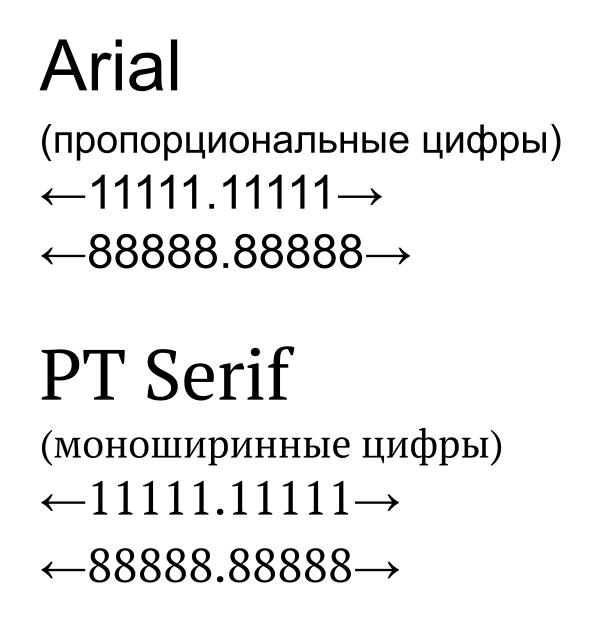
Моноширинный шрифт
Моноширинный, или непропорциональный шрифт, — шрифт, в котором все знаки (точнее, кегельные площадки знаков) имеют одинаковую ширину[1]. Этим он отличается от пропорционального шрифта, в котором буквы отличаются по ширине друг от друга[2].
Следует различать моноширинный и равноширинный шрифты: в последних знаки стремятся к одинаковой ширине, но кегельные площадки знаков неодинаковы[3].
История
Пишущие машинки
Первые моноширинные шрифты были разработаны для пишущих машинок, так как реализация механической печати пропорциональным шрифтом требовала значительного усложнения печатающего узла[4]. Существовали и наборно-печатающие машинки, использующие пропорциональный шрифт и изменение межбуквенных интервалов, но они применялись лишь в оперативной полиграфии[5]. Конструкция электромеханических печатных машинок и телеграфных аппаратов в большинстве своём также предполагала использование моноширинных шрифтов.
Компьютеры
Жизнь моноширинных шрифтов продолжилась на компьютерах: в качестве устройства ввода-вывода во многих ранних ЭВМ использовался телетайп[6][7]. Долгое время алфавитно-цифровые печатающие устройства (например — принтеры типа «ромашка») и знакогенераторы видеотерминалов и графических адаптеров также позволяли использовать исключительно моноширинные шрифты. Текст на экран выводился в виде матрицы знакомест, в которую могло поместиться строго определённое количество знаков (как правило, 80 символов в строке, что соответствовало объёму одной перфокарты), а видеоизображение динамически создавалось по кодам символов и их изображениям — это давало экономию дорогой (в те времена) памяти и упрощало программирование.
В наборы символов подобных устройств часто включались также символы псевдографики для оформления разного рода таблиц и бланков, а также простых графиков и рисунков[8]. В дальнейшем моноширинные шрифты и псевдографика легли в основу расширенного текстового интерфейса пользователя, включающего в себя элементы оконного.
Особенности начертания символов
Буквы многих алфавитов (латинского — в большей степени, современного русского — в меньшей) имеют разную ширину знаков. Некоторые знаки (такие, как i) занимают в кегельной площадке место шириной в один основной штрих, а другие (такие, как w) — в несколько раз больше[3]. Поэтому вокруг узких знаков образуется много пустого места, а широкие становятся тёмными и сложноразличимыми, особенно в небольшом разрешении и жирном начертании.
Чтобы эти недостатки не были столь заметны, к буквам применяются дополнительные меры оптической компенсации. Узким буквам добавляют засечки, даже если остальные символы шрифта выполнены без засечек[4]. У широких символов иногда уменьшают некоторые элементы, как средний штрих у буквы «Ш». Ещё при проектировании моноширинных шрифтов возникает проблема схожести цифры 0 и буквы O, и чтобы их можно было отличить, первую нередко перечёркивают по диагонали, либо вносят другие элементы внутрь овала.
Все эти меры искажают привычный рисунок букв[4]. К тому же строки, набранные моноширинным шрифтом, не выглядят сплошными, а разбиваются на колонки шириной в одно знакоместо, и для компенсации приходится увеличивать межстрочный интервал. Поэтому в больших объёмах текста моноширинные шрифты значительно менее удобочитаемы, чем пропорциональные, и имеют меньшую ёмкость, что делает их малопригодными для книг или журнальных статей[4].
Применение в современной типографике
Несмотря на то, что современные видеосистемы и принтеры компьютеров позволяют работать с пропорциональными шрифтами, моноширинные шрифты продолжают использоваться прежде всего потому, что они предоставляют простой способ форматирования текста, хоть и ограниченный в возможностях, зато не требующий использования специальных языков разметки и программного обеспечения, а также легко воспроизводимый на различных устройствах. Примеры применения моноширинных шрифтов:
- Среды разработки и редакторы исходного текста программ — благодаря использованию моноширинных шрифтов упрощается выравнивание строк и расстановка отступов согласно стандартам оформления, что позволяет лучше ориентироваться в коде[4];
- Интерфейс командной строки и эмуляторы терминала — в них, кроме форматирования вывода, моноширинный шрифт вместе с псевдографикой даёт возможность пользоваться расширенным текстовым интерфейсом пользователя;
- В технической литературе моноширинным шрифтом выделяют любой компьютерный текст — не только блоки исходного кода, но и ключевые слова языков программирования, имена файлов и каталогов, вводимую в программу информацию и т. д.
- В биологии моноширинным шрифтом пишут цепочки нуклеотидов и аминокислот;
- Выполняемые моноширинными шрифтом ASCII-рисунки позволяют менять шрифт на другой моноширинный без особых помех качеству изображения.
- Для печати простых документов вроде кассовых чеков;
- Системы оптического распознавания текста надёжнее работают с моноширинными шрифтами, поэтому такими шрифтами печатают документы, которые, возможно, будут автоматически сканироваться;
- Табулатуры для гитар;
- В западной театральной традиции сценарий печатают шрифтом Courier-12. Одна страница такого сценария длится примерно одну минуту[9][10]. Такой способ оформления до появления компьютеров помогал вносить в сценарий изменения, сохраняя удобочитаемость и единство оформления.
В CSS моноширинный шрифт в общем виде выбирается с помощью конструкции font-family: monospace (хотя можно также указать название конкретного моноширинного шрифта, например font-family: Lucida Console, monospace или font-family: Courier New, monospace).